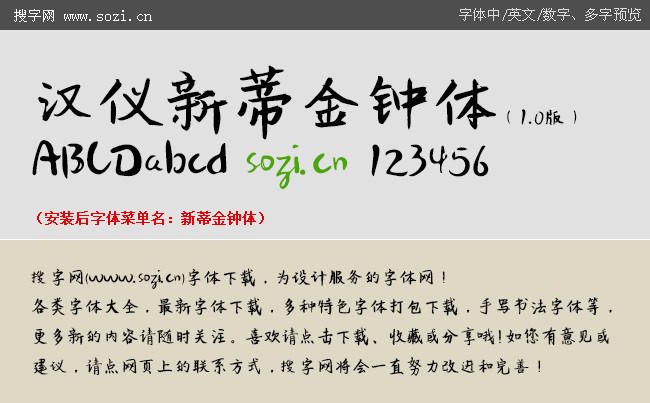
漢儀新蒂金鐘體1.0
搜字網(wǎng)提供一款漢儀新蒂金鐘體1.0字體下載,漢儀新蒂金鐘體是一款非常漂亮的手寫風格藝術(shù)字體。由漢儀新蒂工作室出品,漢儀新蒂工作室成立于2016年,由漢儀字庫與新蒂字體聯(lián)合成立,本字體字形流暢大方,適合應用于海報設(shè)計、藝術(shù)設(shè)計、包裝設(shè)計等應用。(本字體為個人非商用版,如需要商用請聯(lián)系漢儀公司購買版權(quán))